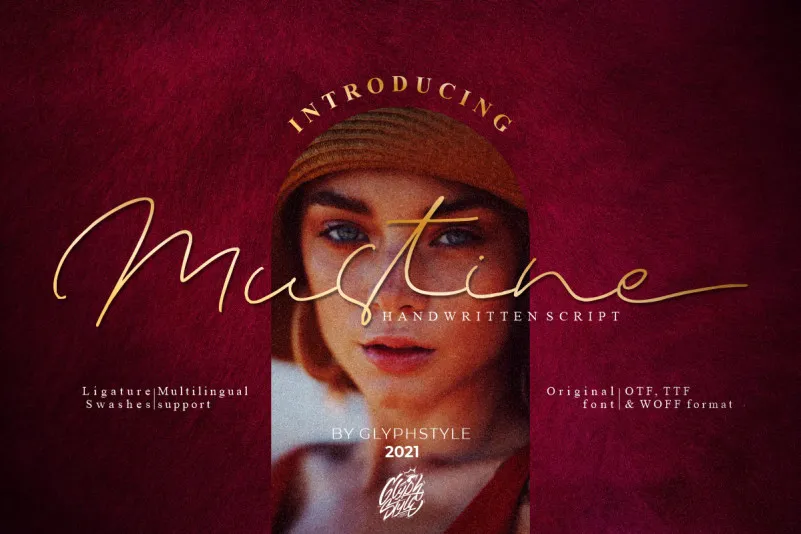
Mustine Font – Download Grátis
Essa é uma fonte naturalmente escrita à mão, com linhas que movem naturalmente para criar uma escrevinhação linda e majestosa. Ideal para aqueles buscando um estilo de escrita autêntico e elegante no design de sua próxima criação. Conhecida como Mustine Font, essa fonte é o trabalho do designer GlyphStyle. Com sua linha fluida e fluída, ela traz uma sensação natural e única que se assemelha a uma letra escrita à mão real, tornando-a perfeita para aplicar em qualquer projeto de design. Seja você um artista digital ou designer gráfico, esta fonte é certamente um recurso valioso para adicionar estilo ao seu trabalho com letras à mão.